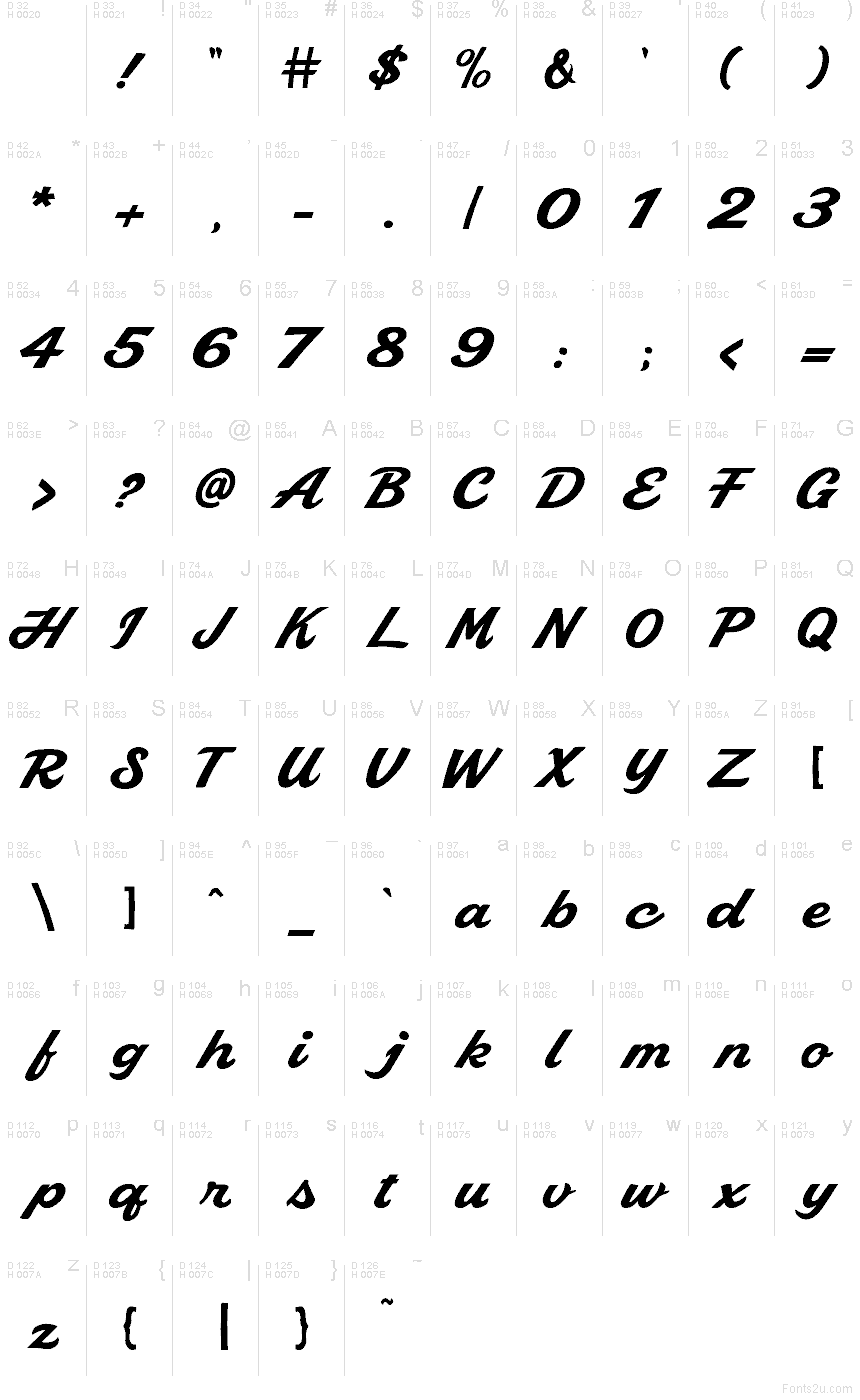
Authentic Declaration od BlackFridayFont je bezplatný font typu brush script s ležérním šmrncem starých ručně malovaných reklamních nápisů. Písmena se plynule naklánějí dopředu, mají široké tahy jako od štětce, těsná spojení a velké počáteční písmeno, což celému fontu dodává rychlý a sebevědomý rytmus.
Skvěle se hodí pro branding, obaly, nadpisy plakátů, menu v kavárnách, obaly alb či titulní karty všude tam, kde chcete rukou psaný efekt namísto uhlazené kaligrafie. Protože jde o bezplatný font, výborně poslouží i pro krátké texty a loga, protože díky výrazné textuře štětce a plynulým spojům působí i krátká slova okamžitě a živě.